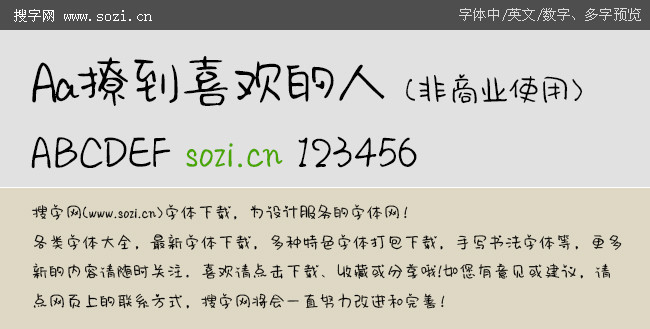
Aa撩到喜歡的人(非商業(yè)使用)
搜字網(wǎng)給大家提供一款A(yù)a撩到喜歡的人(非商業(yè)使用)中文字體下載,該字體是一款手寫(xiě)風(fēng)格的中文字體,字形有趣可愛(ài),并裝飾有心形圖案,適合包裝設(shè)計(jì)、書(shū)裝設(shè)計(jì)、海報(bào)設(shè)計(jì)等應(yīng)用(此字體為個(gè)人非商用版,商用可以聯(lián)系QQ:1006760504)。